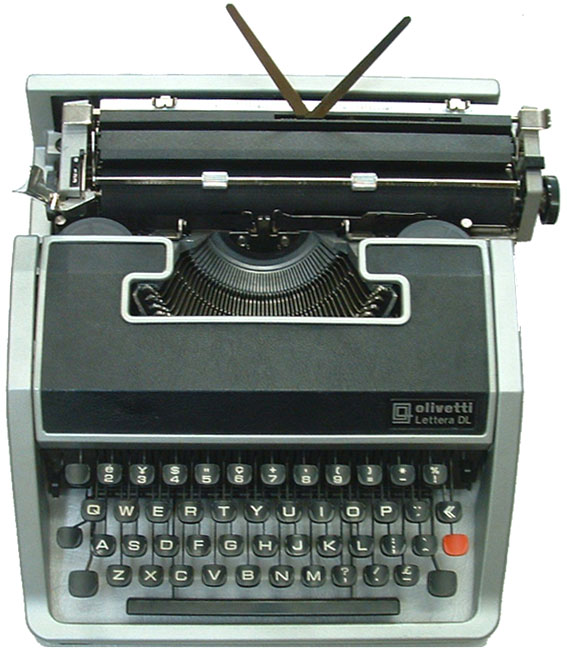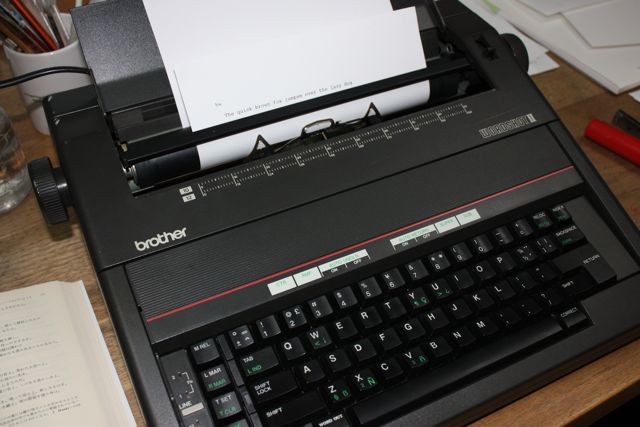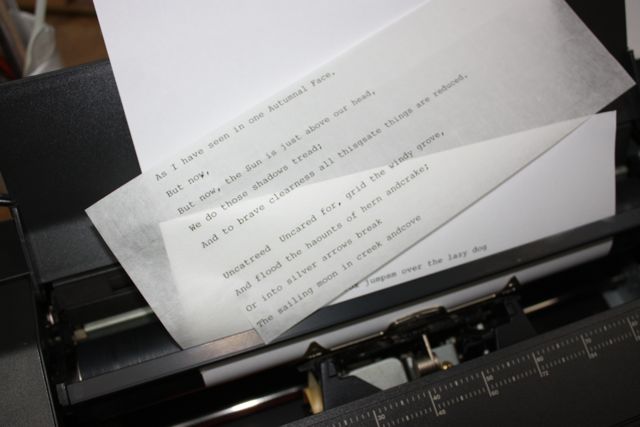
タイプライター
むかーしむかし、中学生だった頃、どうしてもタイプライターが欲しくて、親にねだって買ってもらった事がありました。確か高校の受験合格のお祝いで特別に、ということで買ってもらえたのです。
OlivettiのLettera DL、シルバーで、その当時でもデザインが素敵で本当にカッコよいものでした。電動ではないから、バチバチとかなりの力で叩かなければなりませんでしたが、英語の本を見ながらたくさん打って満足していました。
あの頃から、やっぱり文字が好きだったのかな。それとも英語が好きだったのかな。
結婚して何度も引っ越しをしたので、それももうどこかへ行ってしまいました。でも今また必要になったので、探しましたがどうしてもみつからず、仕方がないのでヤフオクで探していたところ、ちょうど神戸のH子ちゃんから、捨てようと思っていたので引き取って、という朗報が舞い込みました。二つ返事で早速送ってもらったのです。
開けて見てびっくり。とっても状態は良くて、しかも電動!インクリボンもまったく問題なくきれいに印字されます。コピー用紙だけでなく、雁皮の半紙にも打ってみたところ、思った通り美しい!
実はコラージュで使いたいと思ったのです。
書いた文字と印字された文字。両方をひとつにしたら、きっと面白い世界になりそうです。サンプルで貼ってみましたが、これじゃあ貼り過ぎ。もっと効果的に使ってみたいです。
私も同じようなOlivettiのtypewriter持ってました。
懐かし〜い!私は確か大学入学で買ってもらったような
記憶が。おまけにタイピスト学校にまで通いました。
(いまや、そんな学校は存在しない?)
あの頃は、文のセンタリングや表作りは、文字をひとつずつ数えて手作業でした。
typewriterの文字はPCで書いたのと違って、味(人間味?)がありますね。作品、是非見せて頂きたいです。
masayoさんもお持ちでしたか〜!
うふふ、タイプライターはあの音がいいですよね。PCのキーボード叩く音とはヤッパリ違います。
今は復刻版でいろいろとOlivettiの物も出ていますね。インクリボンなどもまだ購入出来る様なので、嬉しいです。
さっそくタイプライターで打った文章を作品に使ってみました。はっきり読め過ぎるので、うまく作品に溶け込ませるようにしなければならず、そこが苦労しました。